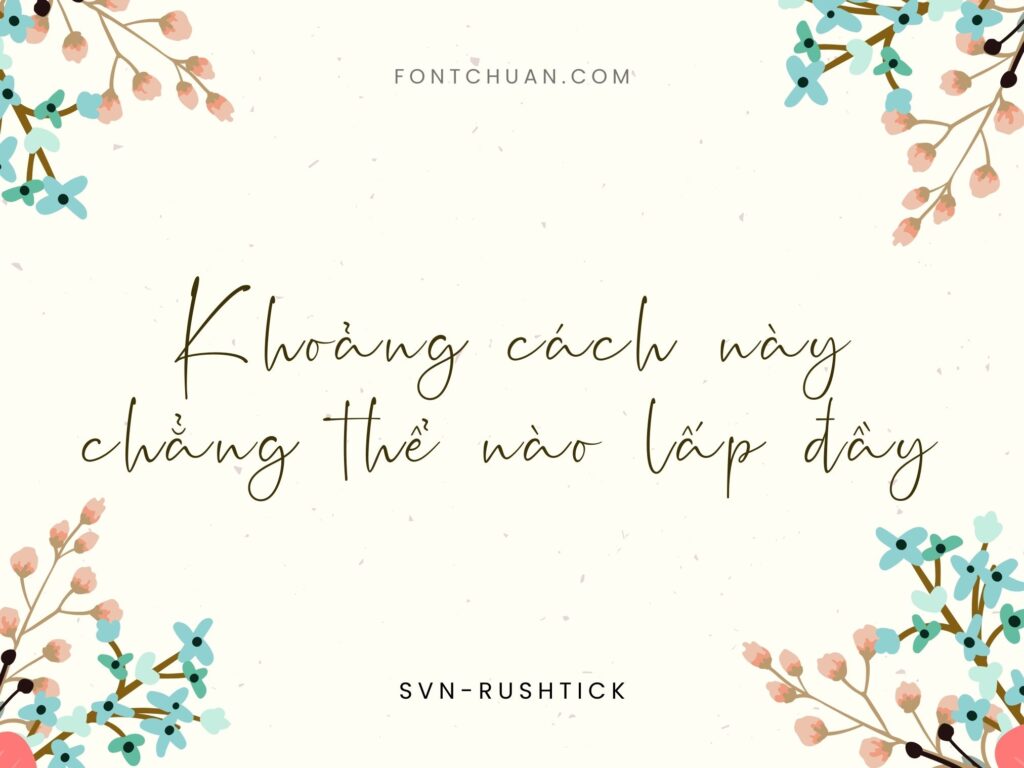
Font SVN Rushtick Việt Hóa
Tác giả Font: Ef Studio
Font SVN Rushtick là phiên bản Việt hóa của kiểu chữ Rushtick, được thực hiện bởi STYLEno.1 Fonts. Rushtick là một font chữ ký mang phong cách viết tay hiện đại, được thiết kế bởi Ef Studio. Font này nổi bật với các nét chữ mềm mại, uyển chuyển, tạo cảm giác tự nhiên và thanh lịch. Rushtick bao gồm đầy đủ các ký tự chữ hoa, chữ thường, chữ số và dấu câu, hỗ trợ đa ngôn ngữ. Font này phù hợp cho nhiều mục đích sử dụng khác nhau như thiết kế logo, tiêu đề, bao bì sản phẩm và các ấn phẩm truyền thông.
SVN Rushtick lý tưởng cho các dự án thiết kế yêu cầu sự thanh lịch và chuyên nghiệp, như thiết kế logo, tiêu đề, bao bì sản phẩm và các ấn phẩm truyền thông. Các ngành nghề như thiệp cưới, giáo dục và bất động sản có thể tận dụng font này để tạo điểm nhấn trong thiết kế. Ngoài ra, font cũng thích hợp cho các sự kiện như Tết, Valentine, Sinh nhật và các lễ hội khác.